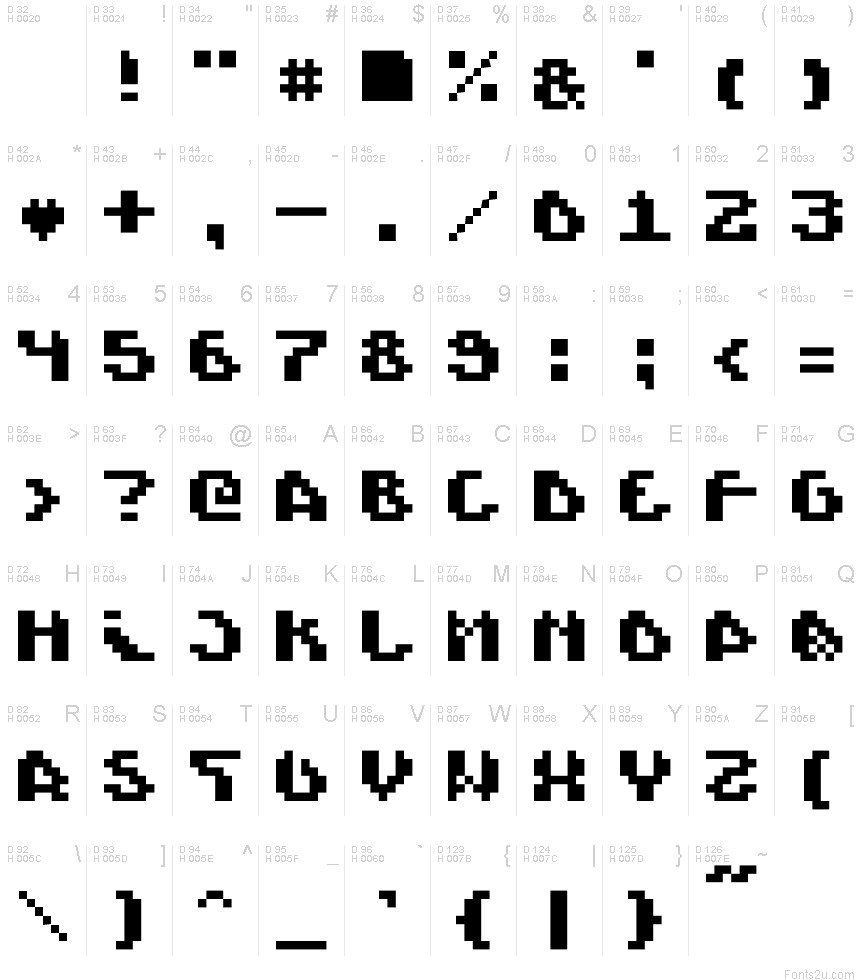
Scienide od Ck! [freakyfonts] je bezplatné bitmapové písmo s ostrým sci-fi vzhledem, který připomíná digitální displeje. Písmena jsou sestavena z masivních čtvercových bloků a ostrých výřezů, což dává písmu rytmus nízkého rozlišení. Působí spíše jako technický signál nebo grafika rozhraní než běžné titulkové písmo.
Přirozeně zapadne do herních log, techno letáků, nadpisů zinů, plakátů a krátkých titulků na obálkách, kde tento digitální švih okamžitě funguje. Jako bezplatný font se Scienide hodí i pro titulní karty, popisné systémy a krátké brandingové prvky, které potřebují pixelovou texturu, aniž by působily roztomile či nostalgicky.